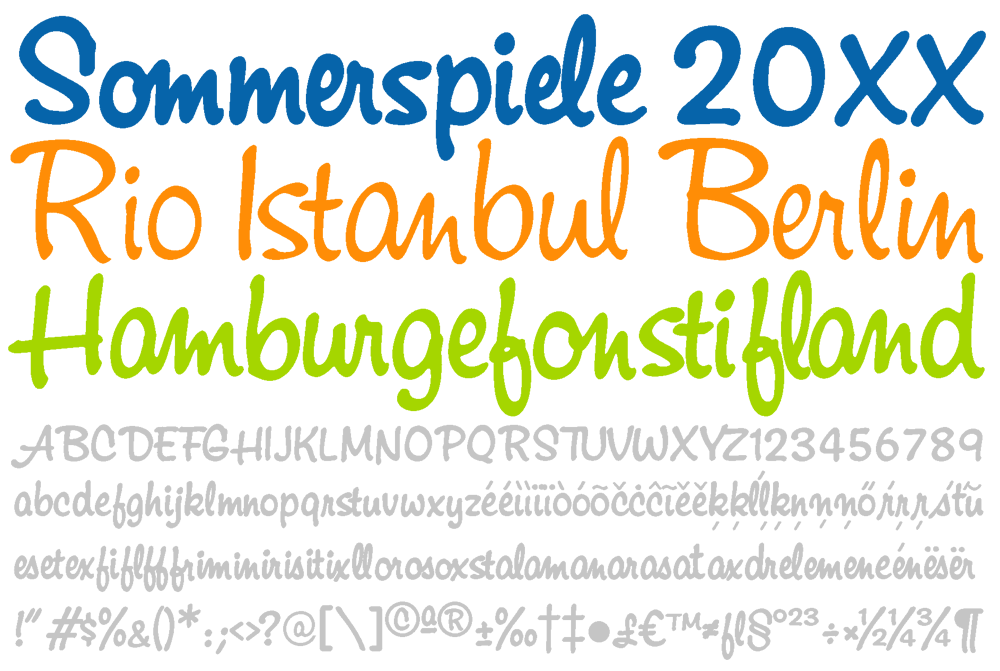
Seit der Vorstellung des Logos für die Olympischen Sommerspiele 2016 in Rio de Janeiro inklusive der dazugehörigen Exklusivschrift ist absehbar: In den kommenden 4 Jahren steht teilverbundenen Filzstift-Schreibschriften eine Blütezeit bevor. Unser Stern der Woche greift diese These auf. Wir haben die Familie Montauk des Hamburger Font-Labels Profonts ausgewäht. Sie ist sicher keine beschwingte Brasilianerin, eher eine informelle, verbindliche Hanseatin. Ihre Sprachkenntnisse sind überragend, was nicht zuletzt die 942 Glyphen pro Font beweisen (komplette Übersicht hier). Die Montauk-Familie setzt sich aus 3 Strichstärken (Light, Regular, Bold) plus den dazugehörigen Oblique-Schnitten (= 6 OpenType-Fonts) zusammen.